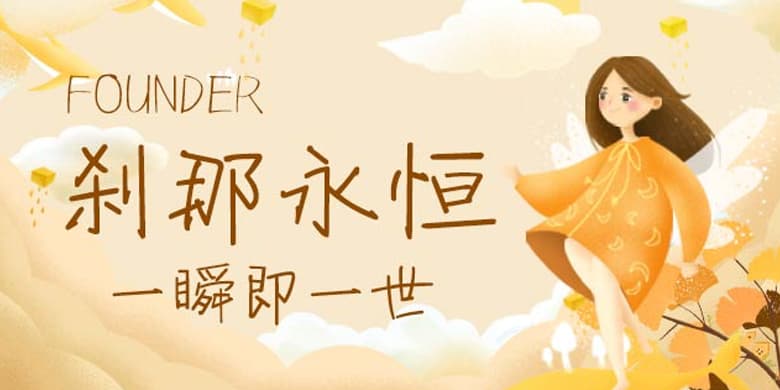
品牌:方正手迹设计师:刘殿儒发行时间:2020字库编码:大陆简体(GB2312-80)分类:常规书写·硬笔字体属性:精品字
刹那永恒体,这款字体笔画遒劲舒展,张弛有度,字形左右延伸,重心平稳,结构典雅自然,风度翩翩,文艺气息浓厚。适用于文艺类的书刊、品牌广告和产品包装设计,综艺影视用字,以及社交网络的个性化用字。